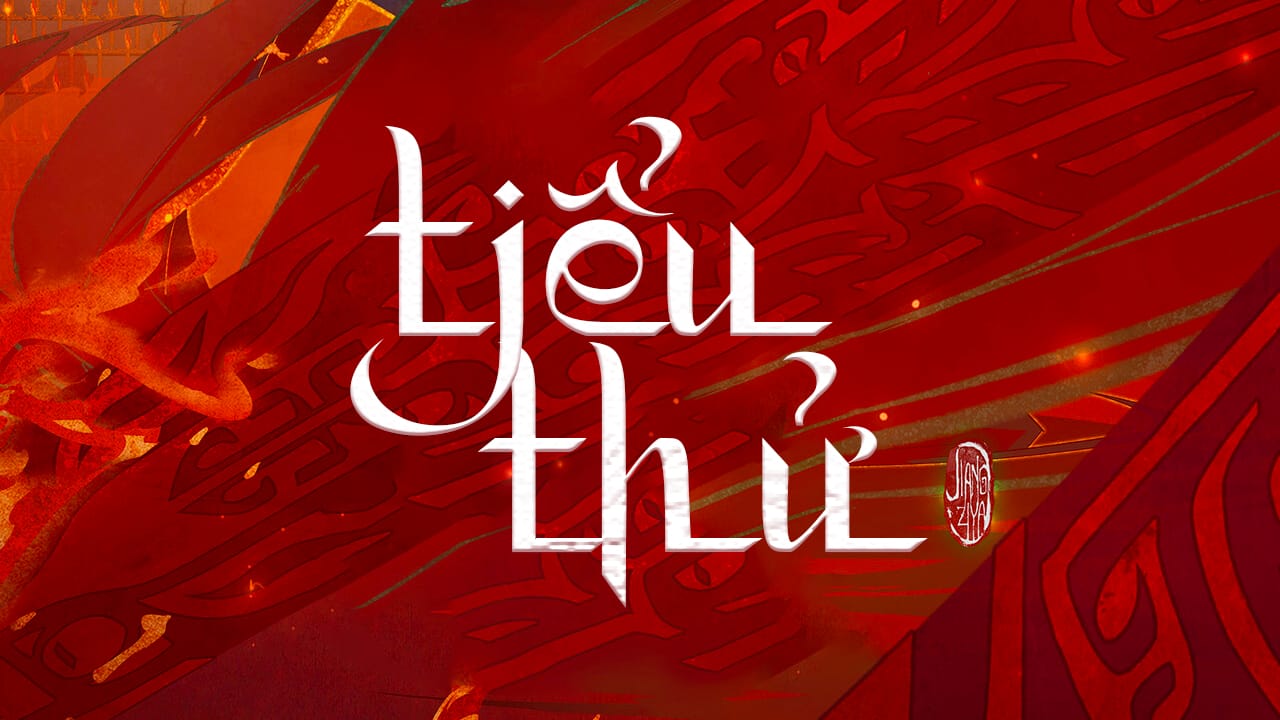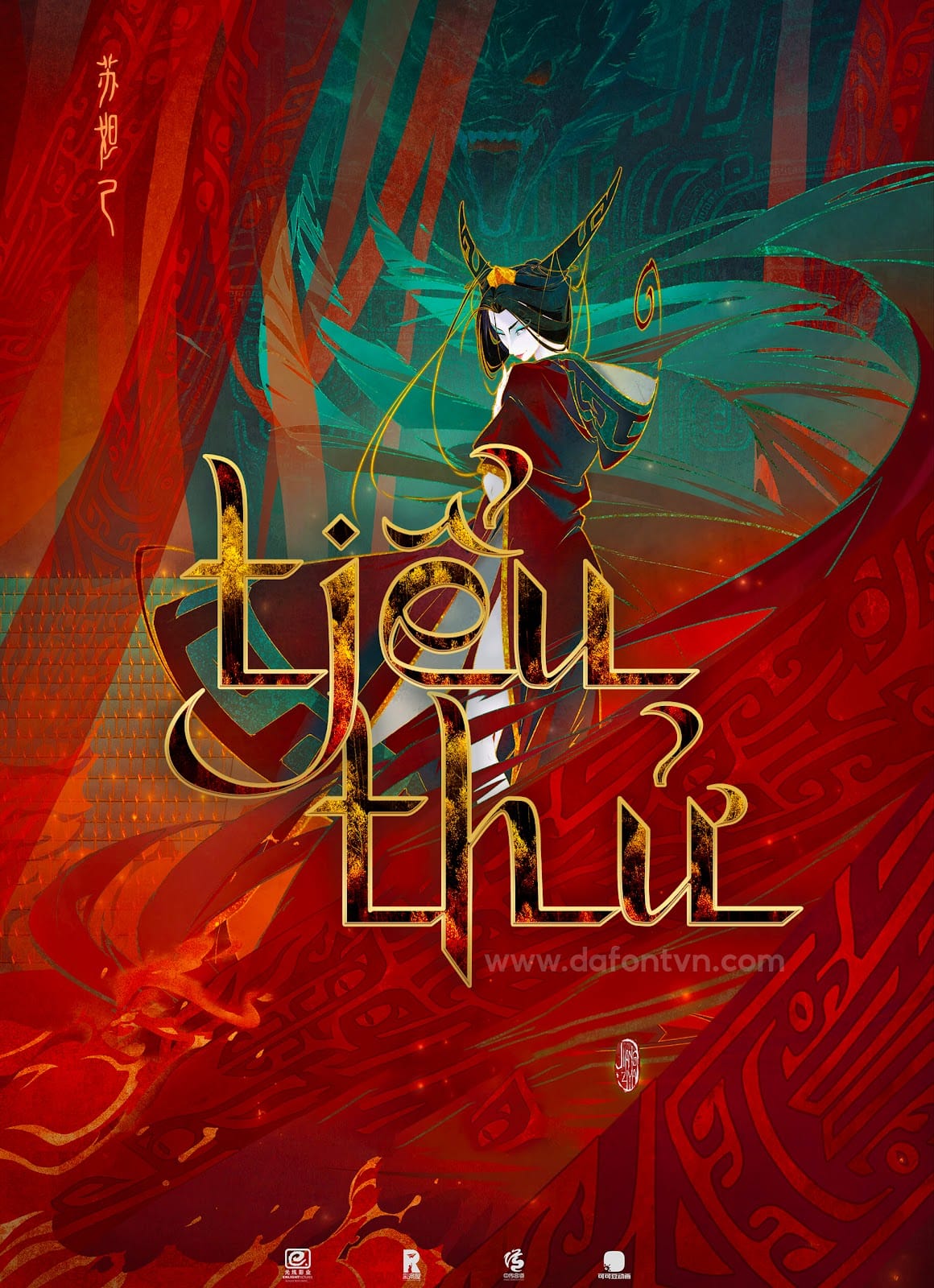
Font chữ cổ trang Việt Hóa – Font Zahra
Đây là font chữ có tên là Zahra được thiết kế theo phong cách Ả Rập khá đẹp. Được kết nối với cách ghép nối để kết hợp tạo ra các thiết bị ấn tượng và phong phú.
Font chữ khá phù hợp cho các thiết kế cổ trang, font Việt Hóa đầy đủ, kerning hoàn chỉnh và đã tối ưu để sử dụng trên điện thoại hoặc máy tính. Font Zahra Việt hóa bởi 1314.